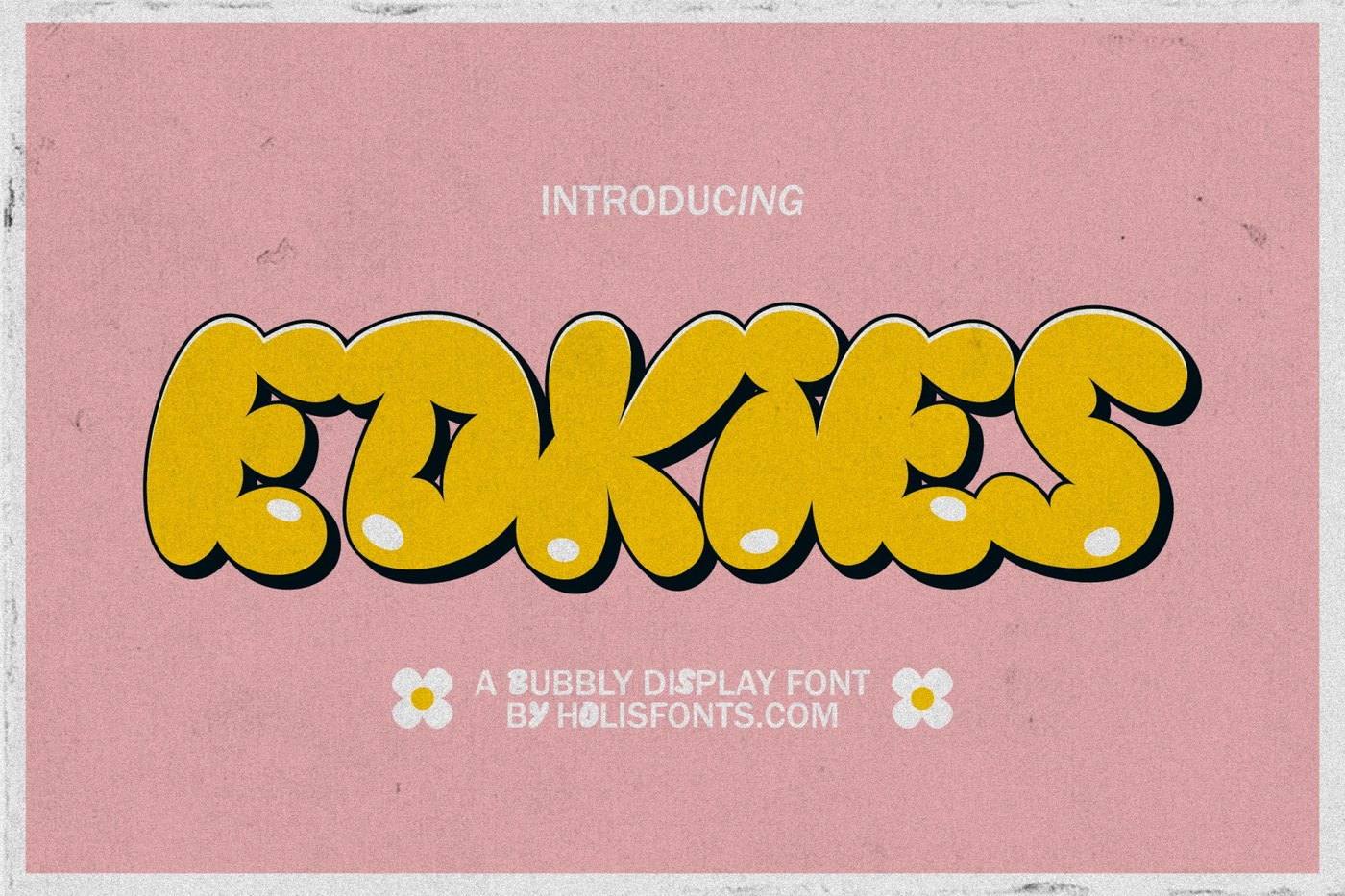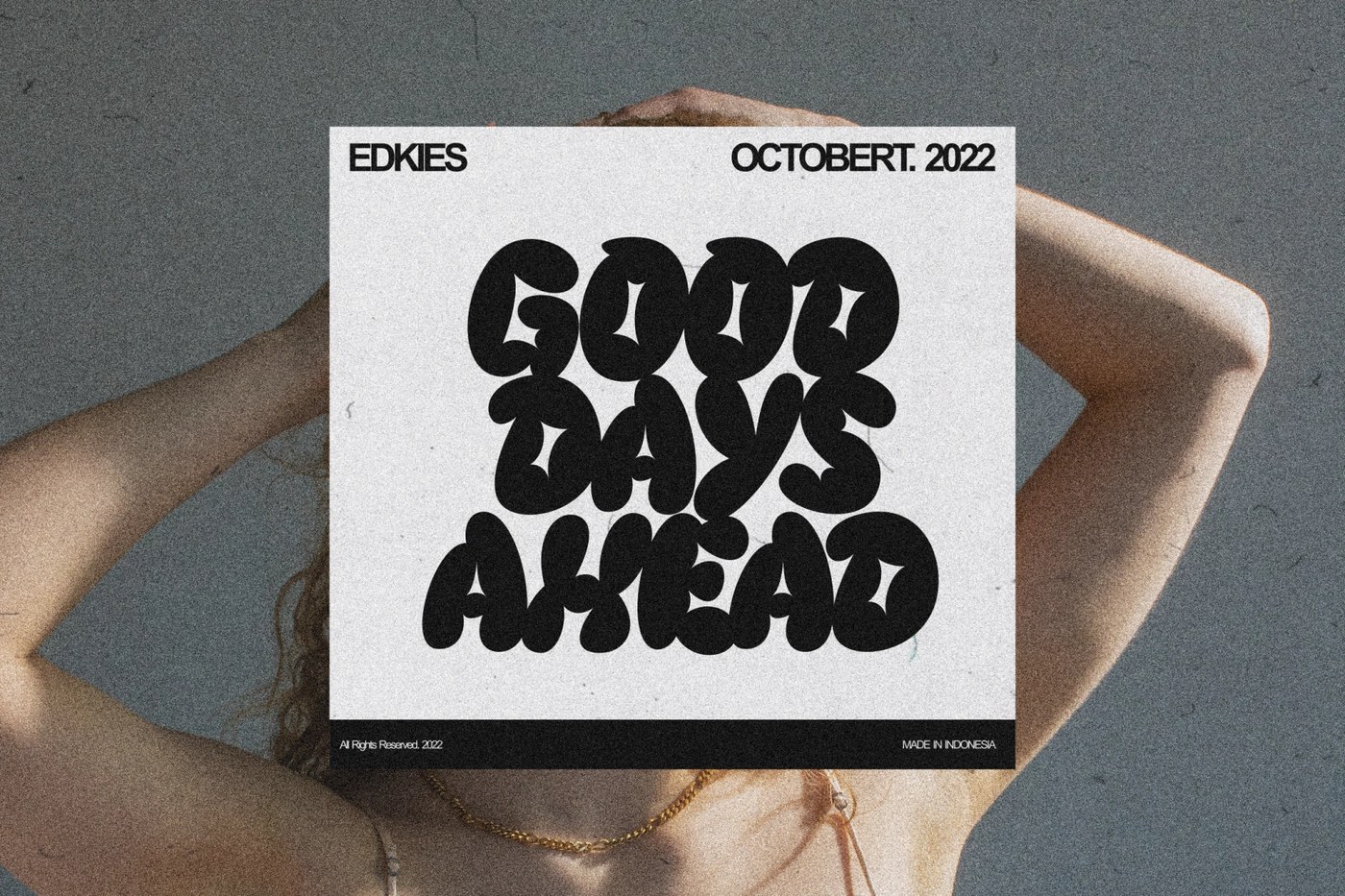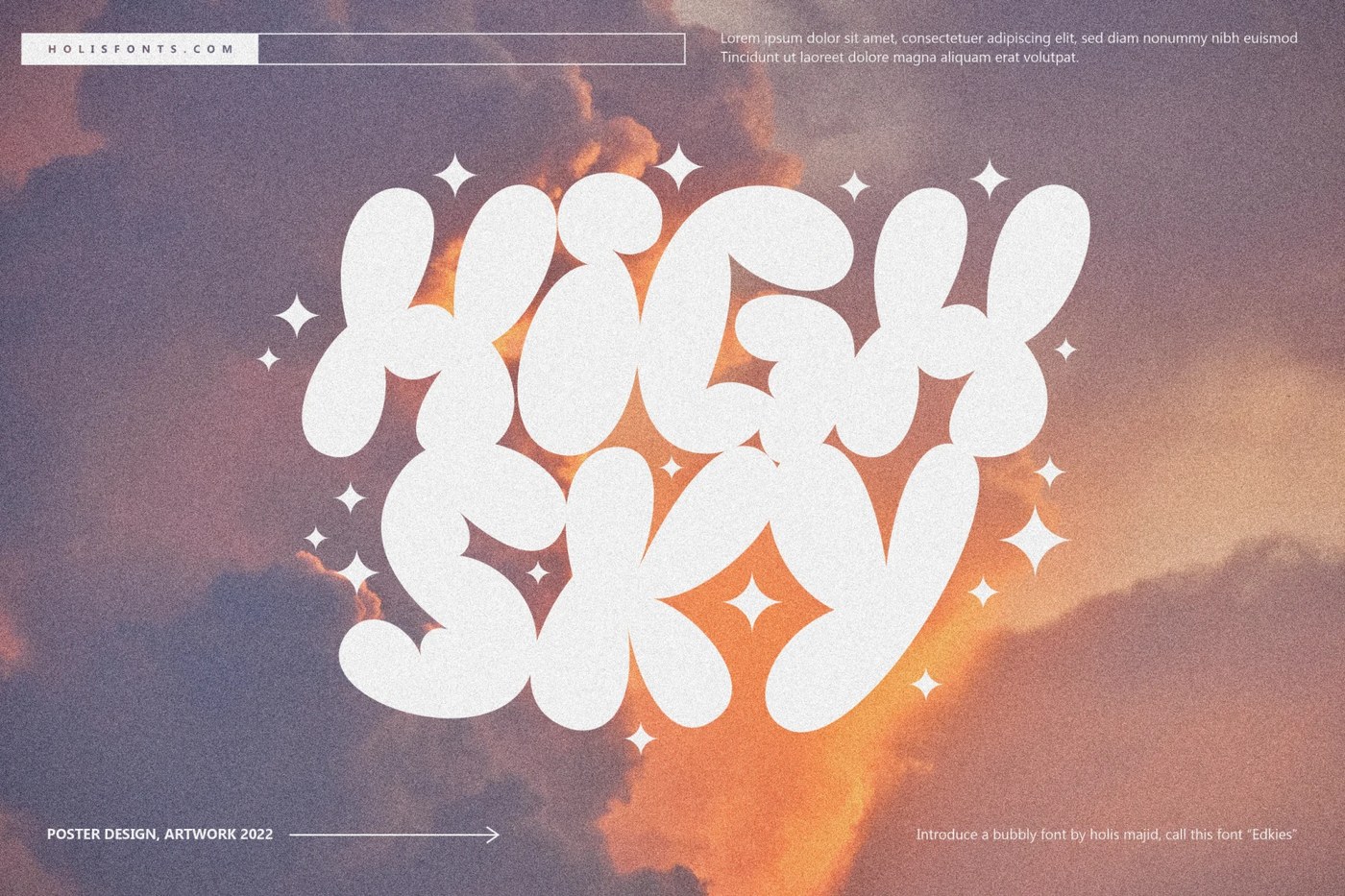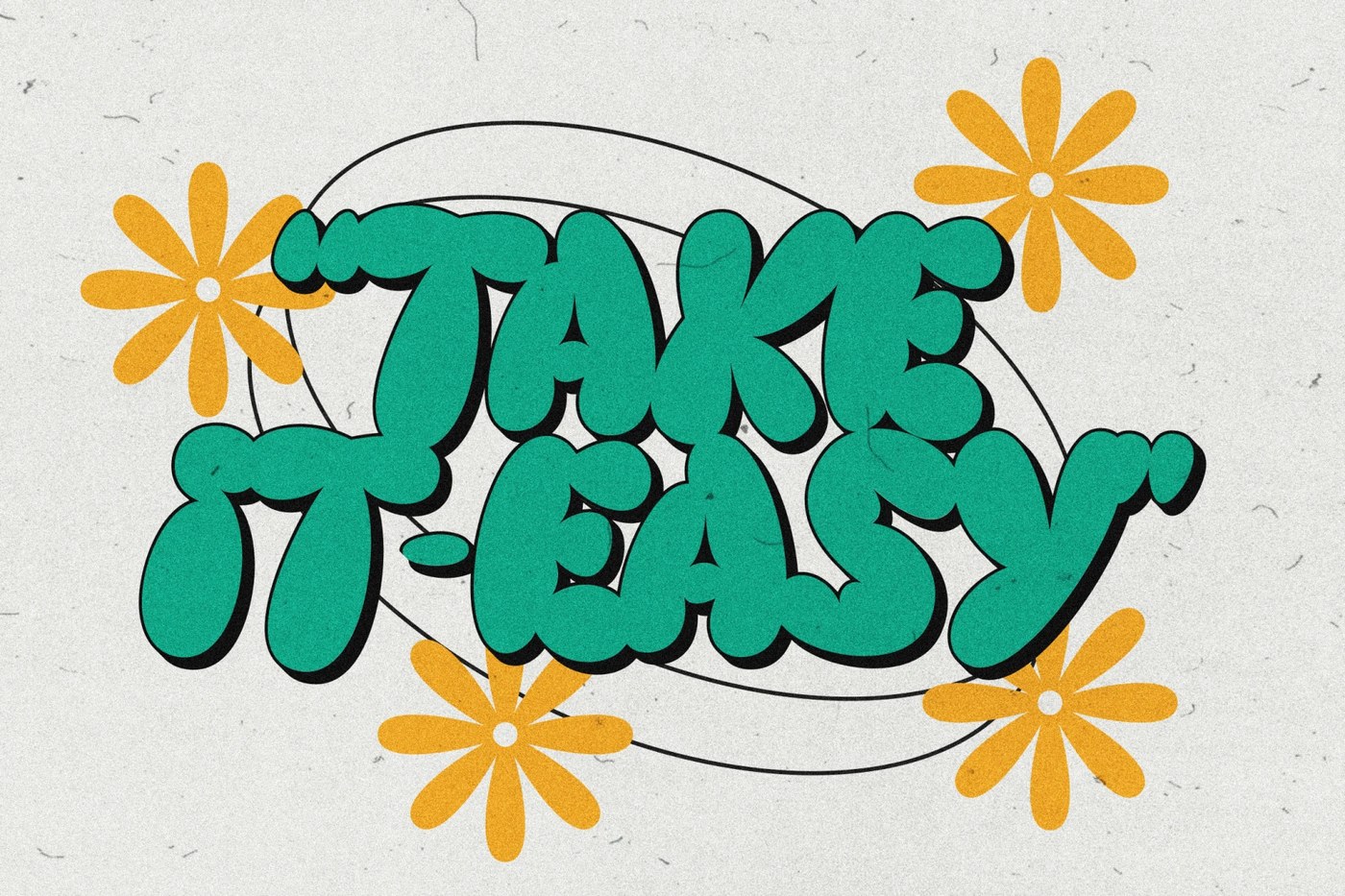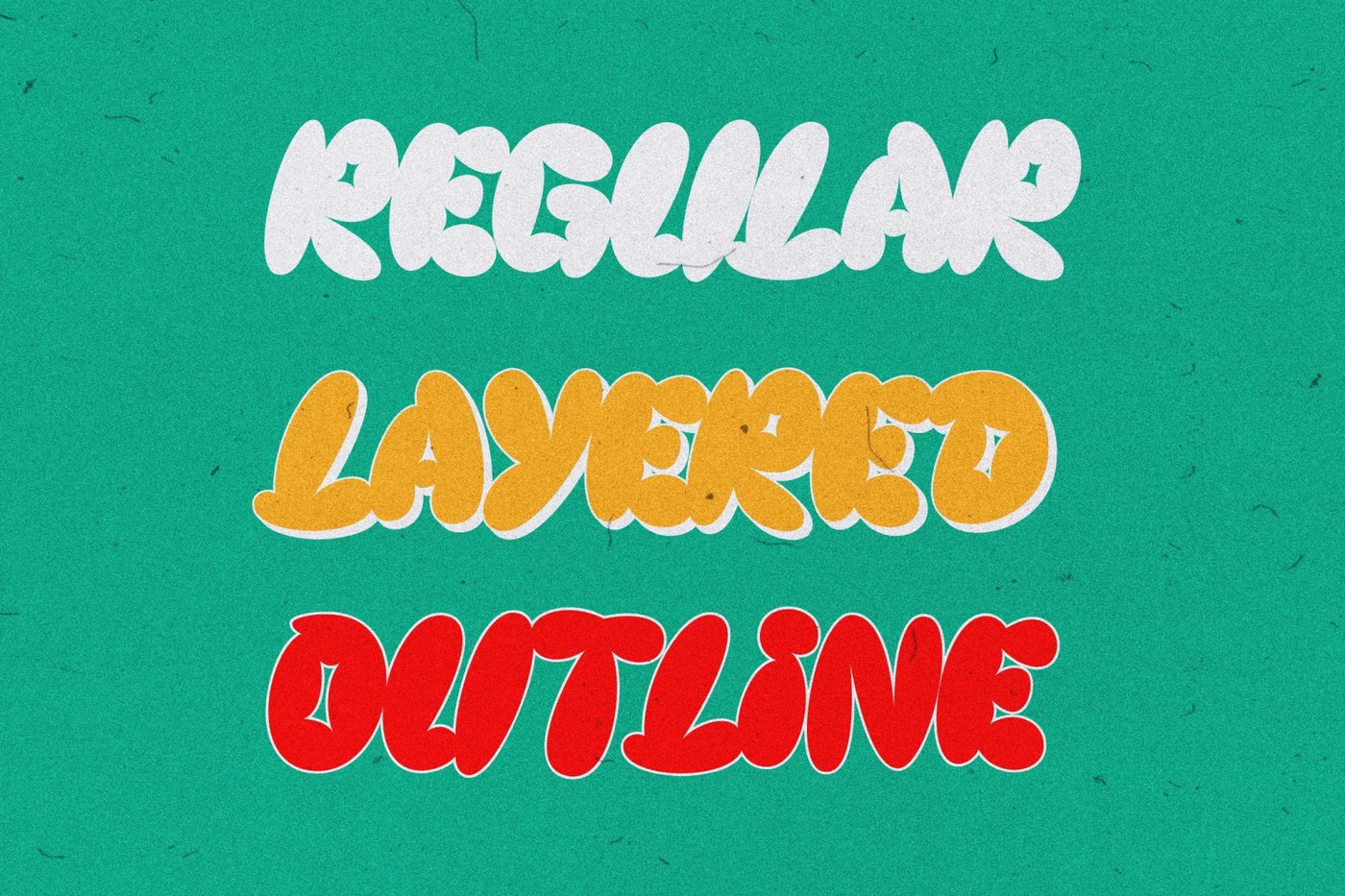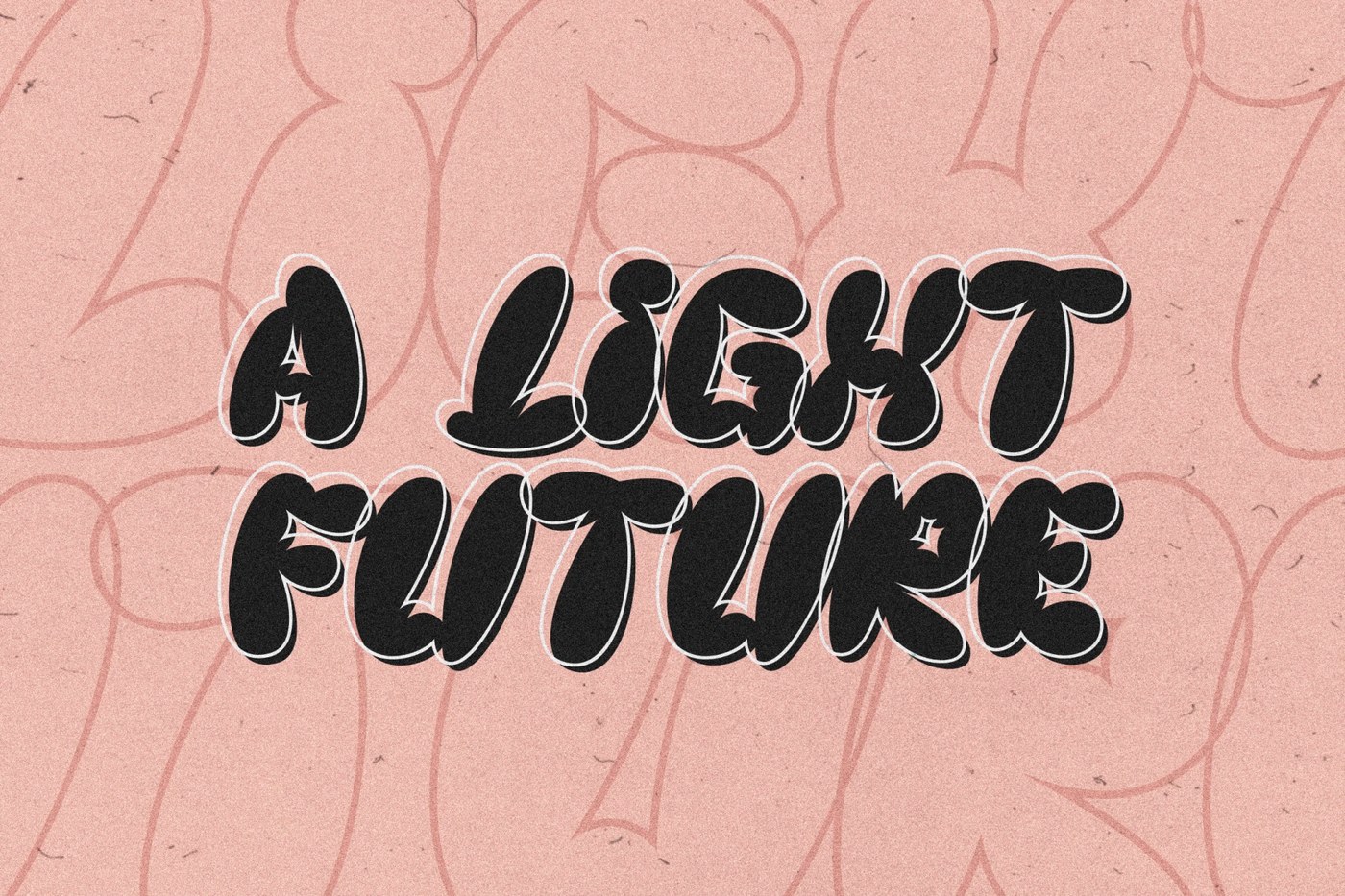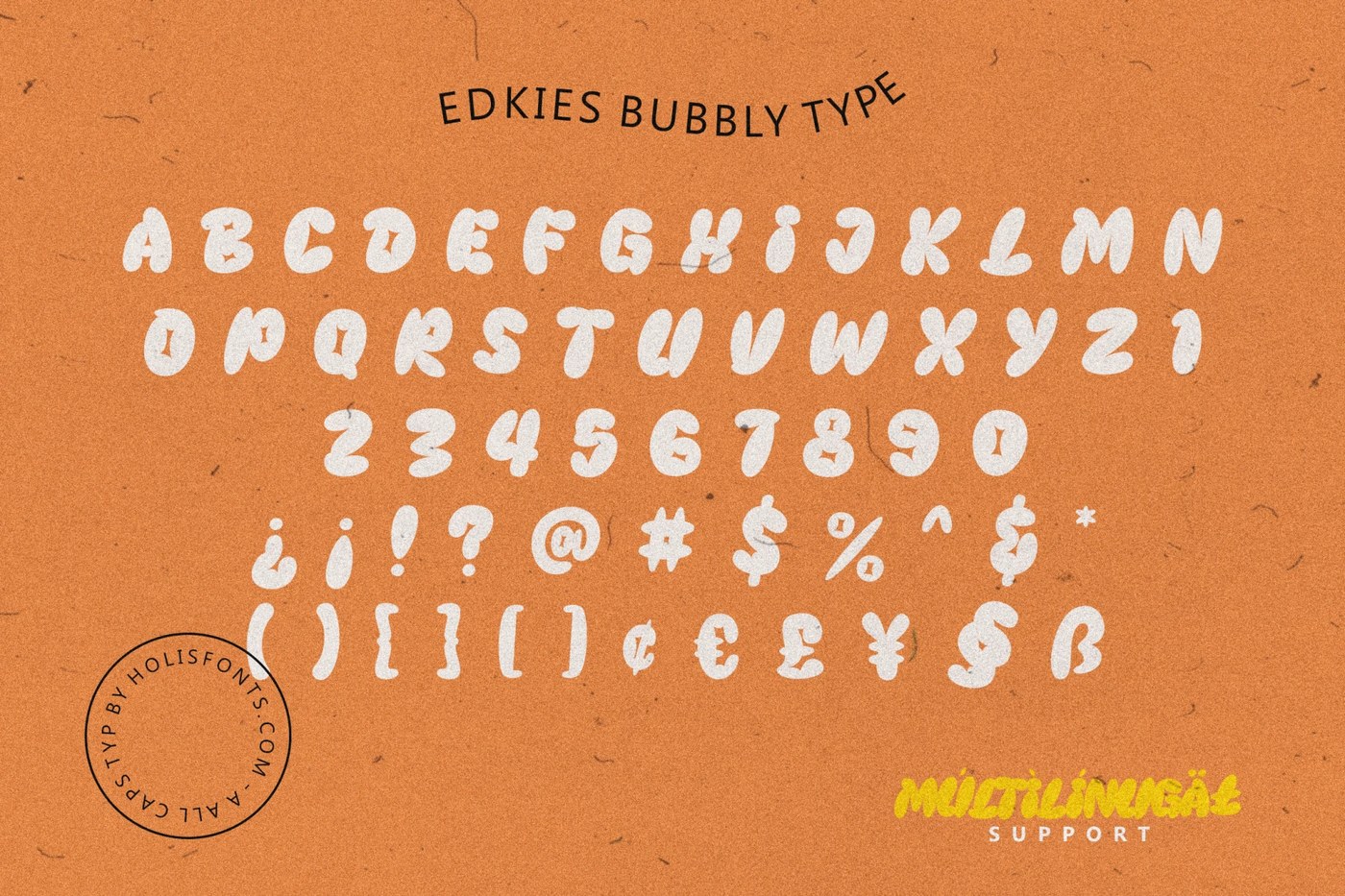
Edkies là một bộ font chữ dạng bong bóng (bubble display font) cực kỳ mũm mĩm được tạo ra bởi https://holisfonts.com và phát hành qua Pixel Surplus. Bộ font này bao gồm ba phong cách chính là Regular, 3D và Outline, có hỗ trợ đa ngôn ngữ và hoàn toàn miễn phí cho các mục đích sử dụng cá nhân.
Điểm nổi bật của Edkies chính là những đường nét bo tròn, căng mọng giúp người xem dễ dàng nhận diện ngay lập tức dù ở khoảng cách xa. Toàn bộ các ký tự trong bộ font này chỉ bao gồm chữ viết hoa (uppercase), điều này giúp tạo nên sự đồng nhất và có chủ đích rõ rệt cho từng con chữ. Cả ba định dạng Regular, 3D và Outline đều có chung tỉ lệ hình thể dày dặn, giúp người dùng có thể dễ dàng xếp chồng các lớp chữ lên nhau hoặc sử dụng độc lập một cách linh hoạt. Trong đó, kiểu 3D tạo hiệu ứng nổi khối mạnh mẽ, còn kiểu Outline lại mang đến vẻ ngoài tối giản nhưng vẫn giữ được khung xương phồng đặc trưng.
Edkies cực kỳ phù hợp cho những dự án cần sự phá cách và cá tính như thiết kế poster, trang phục, bao bì sản phẩm hay các tiêu đề trên mạng xã hội. Việc tập trung hoàn toàn vào bộ chữ in hoa giúp việc sắp xếp bố cục trở nên thuận tiện hơn, đảm bảo sự nhịp nhàng và nhất quán về mặt thị giác trên toàn bộ văn bản. Ngoài các chữ cái, bộ font còn cung cấp đầy đủ hệ thống dấu câu, chữ số và khả năng hỗ trợ đa ngôn ngữ, đáp ứng tốt cho nhiều loại nội dung thực tế thay vì chỉ dừng lại ở các dòng tiêu đề tiếng Anh. Những phong cách thịnh hành như retro hay Y2K đều được thể hiện rất rõ nét qua bộ font này. Hiện tại, font được cung cấp miễn phí cho mục đích cá nhân, còn đối với các dự án thương mại, bạn có thể mua bản quyền trực tiếp tại https://holisfonts.com